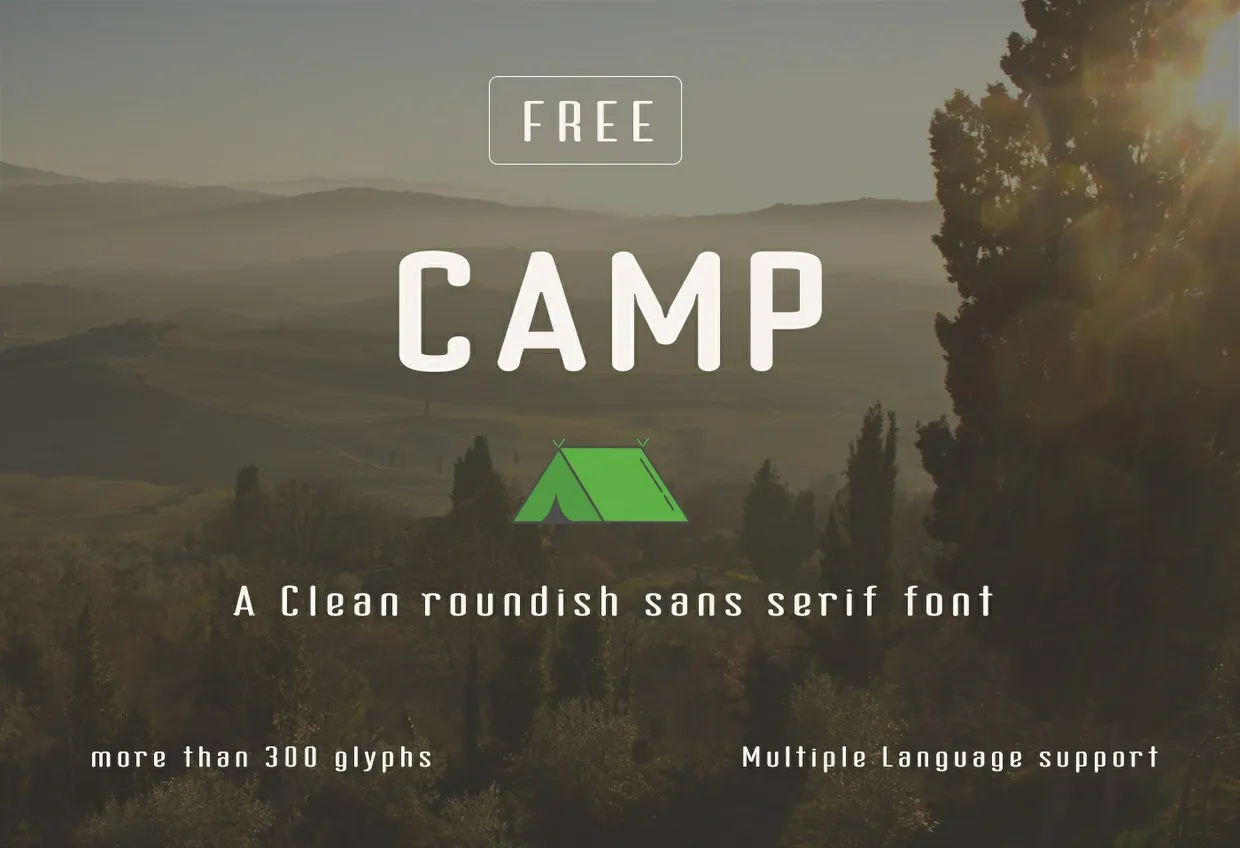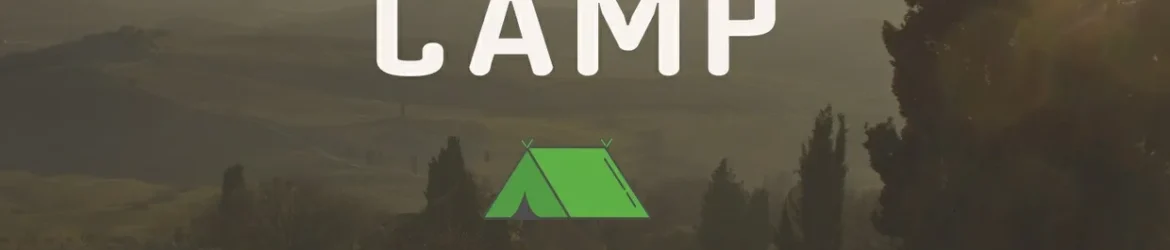
Camp Typeface – Download Grátis
A fonte ‘Camp Typeface’ foi criada por RyanAnthony inspirada nos elementos do ambiente ao ar livre. Com linhas limpas e simples, essa fonte em tipo aberto traz aos comunicadores um toque de aventura e tranquilidade dos espaços ao ar livre. Desenvolvida para projetos que valorizem natureza e descontração, a ‘Camp Typeface’ é uma escolha perfeita para identidades digitais, desde websites e aplicativos até mensagens do WhatsApp ou Instagram. Suas linhas leves e sua forma despojada fazem dela uma fonte versátil e adequada para qualquer uso criativo que busque equilíbrio entre simplicidade e estilo na comunicação digital.